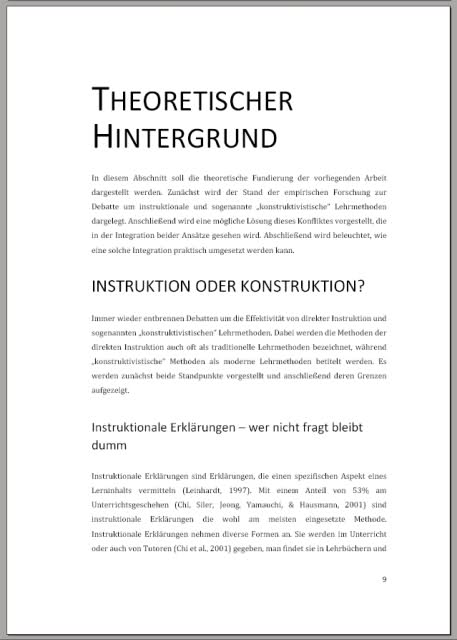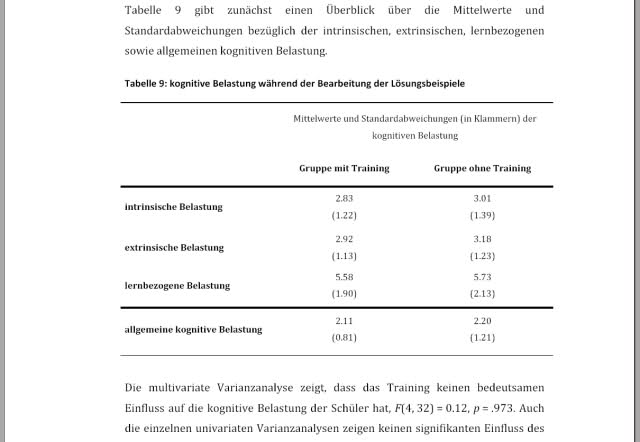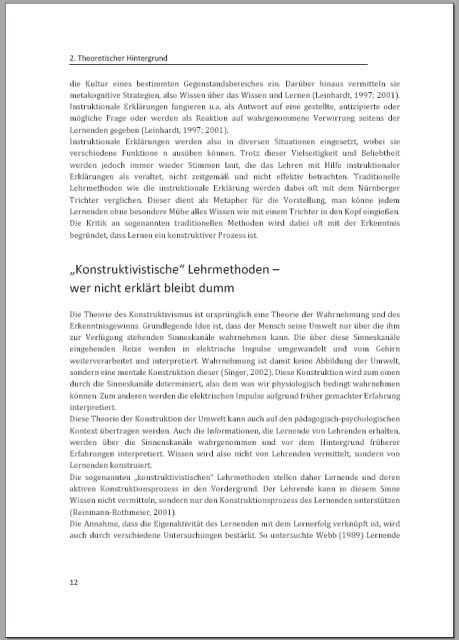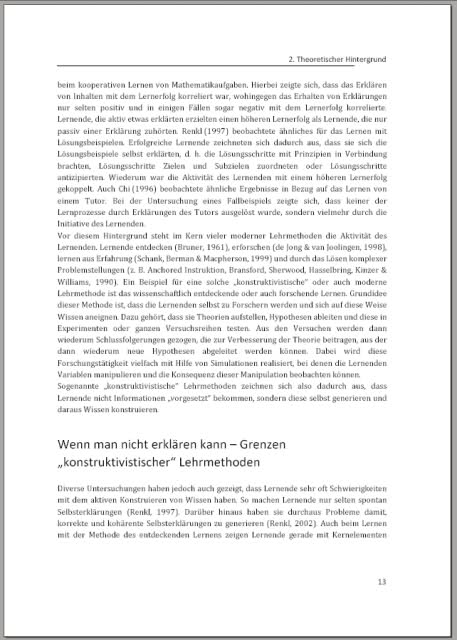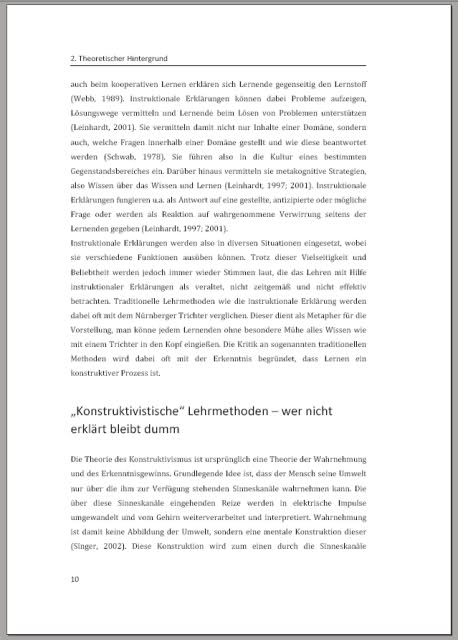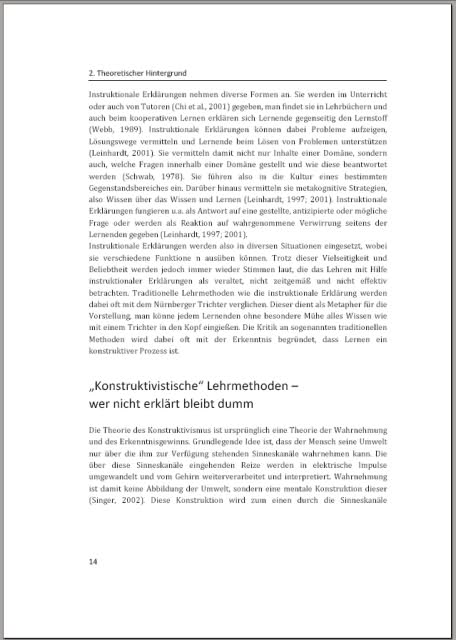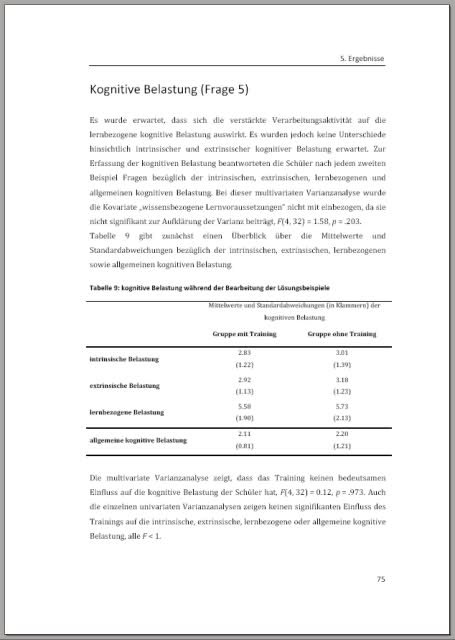
Diplomarbeit - welche Schriftart(en)?
ich schreibe gerade an meiner Diploamrbeit (Psychologie) und bin mitlerweile ziemlich in der Endphase. Da der Inhalt soweit steht, soll nun auch das Äußere in Form gebracht werden. Leider hab ich da üebrhaupt kein Plan was da sinnvoll bzw. angenehm zu lesen ist. Meine Arbeit besteht hauptsächlich aus Text, lediglich im Methoden- und Ergebnisteil wird dieser durch Screenshots, Tabellen oder einige wenige Formeln durchbrochen.
Ich arbeite bisher mit 4 Überschriftebenen, hab die standardmäßig durchnummeriert (außer Ebene 4), würde die Nummerierung aber auch gern weglassen, wenn ihr mir Tips geben könntet, wie ich die Überschriften so gestalten kann,dass eine Numemrierung überflüssig wird.
am besten suchst Du mal in älteren Artikeln, diese Frage taucht hier im Forum mit ziemlicher Regelmäßigkeit auf. Ein Beispiel findest Du hier.
Was die Überschriften angeht: Wirf am besten mal einen Blick in »Erste Hilfe in Typografie« von Willberg und Forssmann. Das Buch ist nicht teuer und Du findest einiges an Material, welches direkt für die Gestaltung Deiner Arbeit (inklusive Überschriften!) relevant ist.
Und ansonsten: bei spezifischeren Fragen einfach noch mal hier nachfragen.
Danke schonmal Christian für deine Hinweise. Ich hatte zwar schon ein wenig im Forum gestöbert, aber dieser Thread war mir nicht untergekommen, da stehen ja schon einige hilfreiche Sachen drin.
Ich hab mich jetzt für Cambria (Fließtext) und Calibri (Überschriften) entscheiden, diese Kombi wurde irgendwo anders hier im Forum vorgeschlagen. Am Bildschirm fand ich die Cambria zwar ziemlich hässlich, aber ausgedruckt hat sie mir ganz gut gefallen.
Ich hab mal nen drei screenshots meiner Arbeit hochgeladen, falls jemand nen Blick drauf werfen will.
Also, so ganz spontan und nach den (zu kleinen) Bildern zu urteilen gefällt mir das eigentlich gar nicht schlecht! Sofort positiv aufgefallen ist mir z.B., daß Du eine der typischen Sünden vermieden hast, nämlich die Seitenzahl außen und den lebenden Kolumnentitel innen zu platzieren. Diese Anordnung ist meiner Erfahrung nach bei der Mehrheit der Arbeiten anzutreffen und ergibt natürlich keinen Sinn, denn man muß die Arbeit komplett aufschlagen um den Kolumnentitel lesen zu können, der aber ja normalerweise zum schnellen Auffinden da ist.
Zu meckern gibt es natürlich (fast) immer. So hast Du für die Hauptüberschrift falsche Kapitälchen gewählt. Du schreibst vermutlich in Word oder OOffice? Die Cambria hat schon echte Kapitälchen, die lassen sich allerdings in Word leider nicht ansprechen – ein wirklich großes Ärgernis! Mich stören falsche Kapitälchen gewaltig und ich persönlich würde dringend zu einer anderen Lösung raten, aber ich kenne auch genügend Leute, die das nicht stört.
Weiterhin sticht die Hauptüberschrift zumindest auf der Abbildung sehr stark hervor. Ist sie fett? Das ist immer so eine Sache: Doppelte Hervorhebunben. Bei der dritten Ebene gefällt mir das recht gut, insbesondere die erste Ebene finde ich allerdings zu schwarz im Vergleich zum Rest. Eine große Schrift zeichnet doch schon aus, muß es auch noch fett sein? Falls sie nicht fett ist würde ich mal versuchen, sie abzutönen, vermutlich macht sich ein dunkles grau am besten.
Weiterhin sollten Versal- und Kapitälchen-Zeilen leicht gesperrt werden, sonst werden sie so »fleckig« wie auf Deiner Abbildung! :)
Im Moment erscheinen zudem die Abstände zwischen Überschrift und Text auf beiden Seiten (also nach oben und unten) gleich zu sein. Normalerweise gliedert es einen Text deutlich besser, wenn die Überschrift an den zugehörigen Text heran gerückt wird, wenn also der Abstand zum vorhergenden Kapitel größer ist.
Die Überschriften hast Du sehr schön im Flattersatz gehalten (im Gegensatz zum Blocksatz des Haupttextes). Hier würde ich aber dringend zum sinnvollen Umbruch raten.
»Instruktionale Erklärungen – wer nicht fragt bleibt
dumm«
Ist so ein Beispiel. Das »bleibt« steht da etwas einsam und verloren am Ende der Zeile – wenn man es mal laut liest, dann wird klar, daß man automatisch eine Zäsur nach »fragt« macht. Wenn man dann auch hier die Zeile bricht, dann liest es sich gleich viel angenehmer.
Die Tabelle gefällt mir noch am wenigsten, da »kleben« die Linien noch zu sehr am Text. Allerdings ist sie etwas zu klein um hier wirklich konstruktive Anregungen geben zu können. Tabellen werden allerdings auch in »Erste Hilfe …« behandelt bzw. noch besser in »Lesetypografie« (sollte in der Uni-Bibliothek zu kriegen sein). Zur Not kann ich Dir auch noch einen recht netten Artikel dazu schicken (den Namen des Autors nenne ich jetzt nicht, sonst kriege ich von Norbert II. wieder was zu hören! :P ).
Sind übrigens die Seitenränder vorgegeben? Ich persönlich würde nach Augenmaß die Aufteilung ja minimal nach oben rücken und unten mehr Luft geben. Dann paßt zwar nicht mehr so viel auf eine Seite aber es sieht besser aus.
Die Arbeit an sich sieht doch schon sehr schön aus. Glückwunsch. Aber die ersten beiden Überschriftenebenen sind definitiv zu groß, es wirkt schon fast wie Zeitschriftentypo. Versuche die Unterschiede, vor allem in der Größenabstimmung geringer zu halten und lieber mit fetten Typen, der Anordnung (zb. Text einrücken und Überschriften normal) oder dem Abstand Struktur zu gewinnen.
Nochn kleiner Nachtrag. Versuche die Überschriften näher an den Text zu bringen, auf den diese sich beziehen. Im Moment hängen sie noch zwischen oberem und unterem Absatz herum (erstes Blatt)